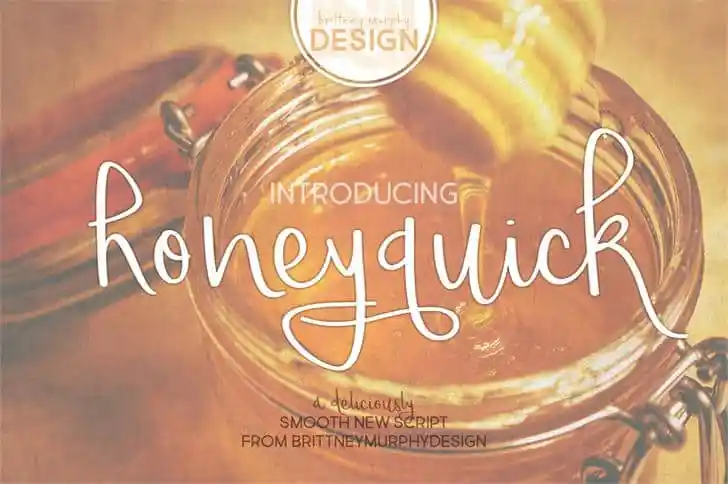
Untitled Script Font – Download Grátis
Aqui está uma versão em português para a descrição do download da fonte “Untitled Script Font”, criada pelo designer Brittney Murphy Design: A fonte “Untitled Script Font” é um encantador conjunto de letras feitas à mão que traz uma sensação natural e suave. Com suas linhas fluidas e características elegantes, ela se adequa perfeitamente a qualquer projeto onde você deseja adicionar um toque delicado e personalizado às suas criações digitais. Brittney Murphy Design é conhecida pela sua habilidade de criar fontes de letra que remetem à arte manual em uma plataforma digital. “Untitled Script Font” é um excelente exemplo disso, com seus traços fluidos que parecem ser capazes de se adaptar a qualquer design e proporcionando liberdade para que você crie personalidades únicas dentro do seu trabalho. Para os amantes da fonte e dos designers digitais que procuram uma opção suave e versátil para seus projetos pessoais, esta font é perfeita. Para quem está buscando incorporar a fonte em um projeto comercial, Brittney Murphy Design oferece licenças disponíveis na sua página oficial. Não se preocupe! Com o seu uso personalizado gratuito permitido, você pode começar a explorá-la agora. Essa fonte não apenas traz beleza e originalidade para seus designs digitais, mas também mantém um preço acessível que torna a inclusão dela em qualquer projeto uma opção viável.
Designer: Brittney Murphy Design